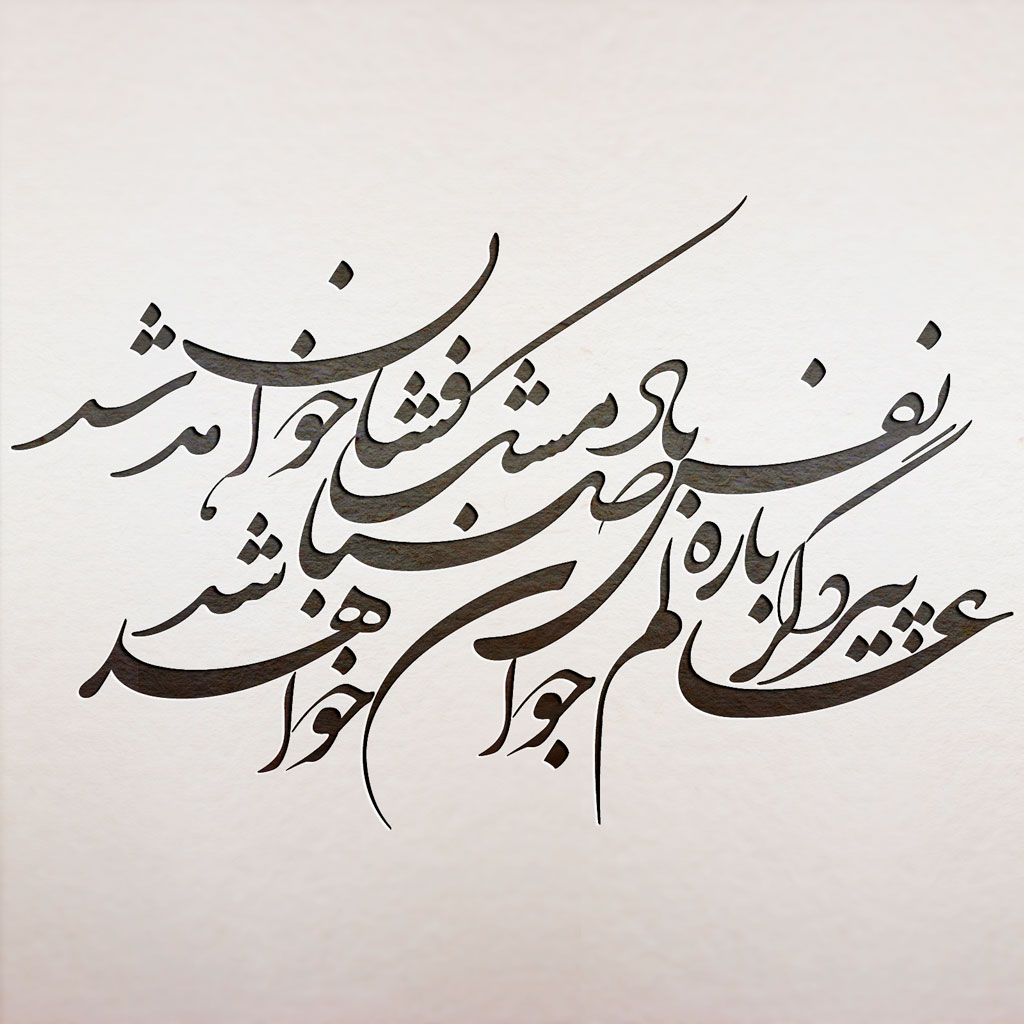
دنبال یه فونت هستم که وقتی می نویسم برام گردش کنه یعنی اینکه می خوام بزارمش داخل یه دایره که نوشته کلش رو پوشش بده
اگر انگلیسی میخوای از همین وبلاگ فونت Logomotion رو دانلود کن
فارسی لازم دارم
می خوام برای بنر های هیئت لوگو درست کنم :)
فکر کنم نستعلیق و شکسته به کارتون بیاد، سبک فونت رو بگید تا راهنمایی کنم
پروفایلش لوگو ی هیئت چادر خاکی هست مثل اون می خوام
فونت ایران نستعلیق رو دانلود کن
با آدوس طراحیش کردی؟